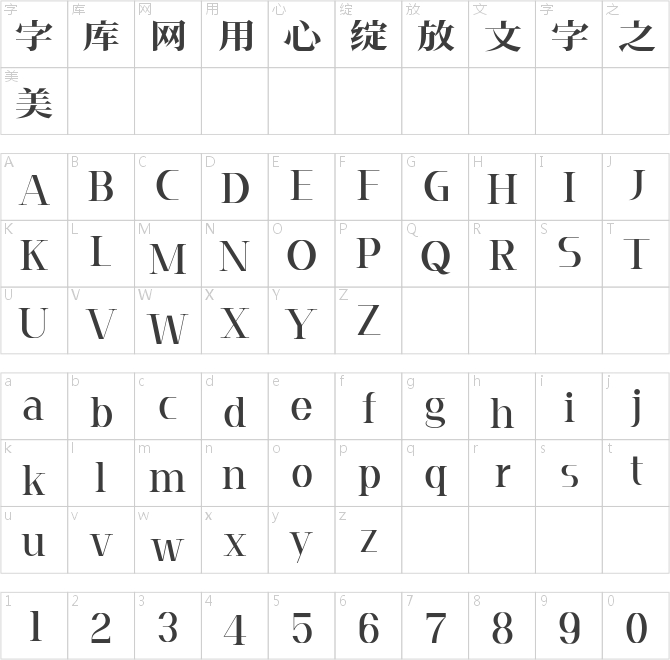
字魂獨(dú)角獸體
字魂獨(dú)角獸體,由字魂新開發(fā)的電腦字體,這款字體看上去精簡(jiǎn)干練,簡(jiǎn)約的同時(shí)又不失設(shè)計(jì)感!適合應(yīng)用于藝術(shù)設(shè)計(jì)、平面宣傳設(shè)計(jì)、網(wǎng)頁設(shè)計(jì)等領(lǐng)域,需要的朋友可以前來字魂官網(wǎng)下載授權(quán)使用。